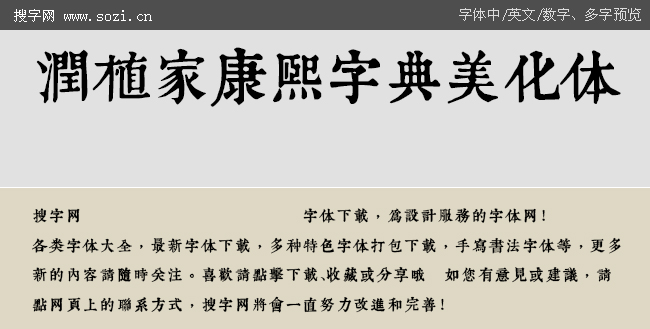
潤(rùn)植家康熙字典美化體
搜字網(wǎng)給大家提供一款潤(rùn)植家康熙字典美化體中文字體下載,該字體是一款宋體字體,由潤(rùn)植家字庫(kù)出品,字體筆觸適中,字形端正,根據(jù)康熙字典字體特點(diǎn),生造或美化諸多字形,適用于兒童海報(bào)設(shè)計(jì)、網(wǎng)頁(yè)設(shè)計(jì)、包裝設(shè)計(jì)等應(yīng)用。